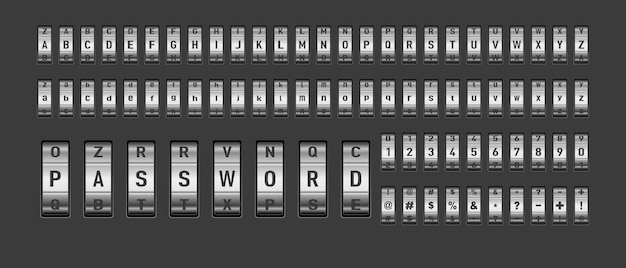
Шрифт кодового замка. Реалистичный механический код. Вращающийся алфавит. Набор металлических колес банковского сейфа с буквами и цифрами. Секретные опции. Набор вращающихся элементов. Варианты знаков открытия векторного хранилища.Шрифт кодового замка. Реалистичный механический код. Вращающийся алфавит. Набор металлических колес банковского сейфа с буквами и цифрами. Секретные опции. Набор вращающихся элементов. Варианты знаков открытия векторного хранилища.
Шрифт кодового замка. Реалистичный механический код. Вращающийся алфавит. Набор металлических колес банковского сейфа с буквами и цифрами. Секретные опции. Набор вращающихся элементов. Варианты знаков открытия векторного хранилища.